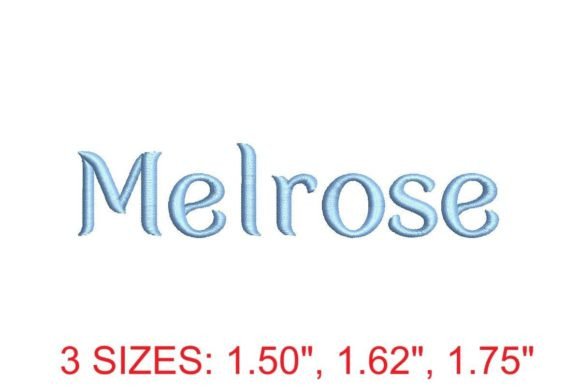
Melrose Font
Nếu bạn đang tìm kiếm các tài nguyên chất lượng cao như Melrose Font, gói cao cấp này là một lựa chọn tuyệt vời cho các dự án sáng tạo của bạn.
Được chế tác với độ chính xác cao, Melrose Font cung cấp các vector sạch, kiểu chữ mượt mà và giấy phép thương mại để bạn yên tâm.
Cho dù bạn đang tạo sản phẩm POD (In theo yêu cầu), thiệp mời đám cưới hay đồ họa mạng xã hội, Melrose Font đều là một sự lựa chọn lý tưởng.